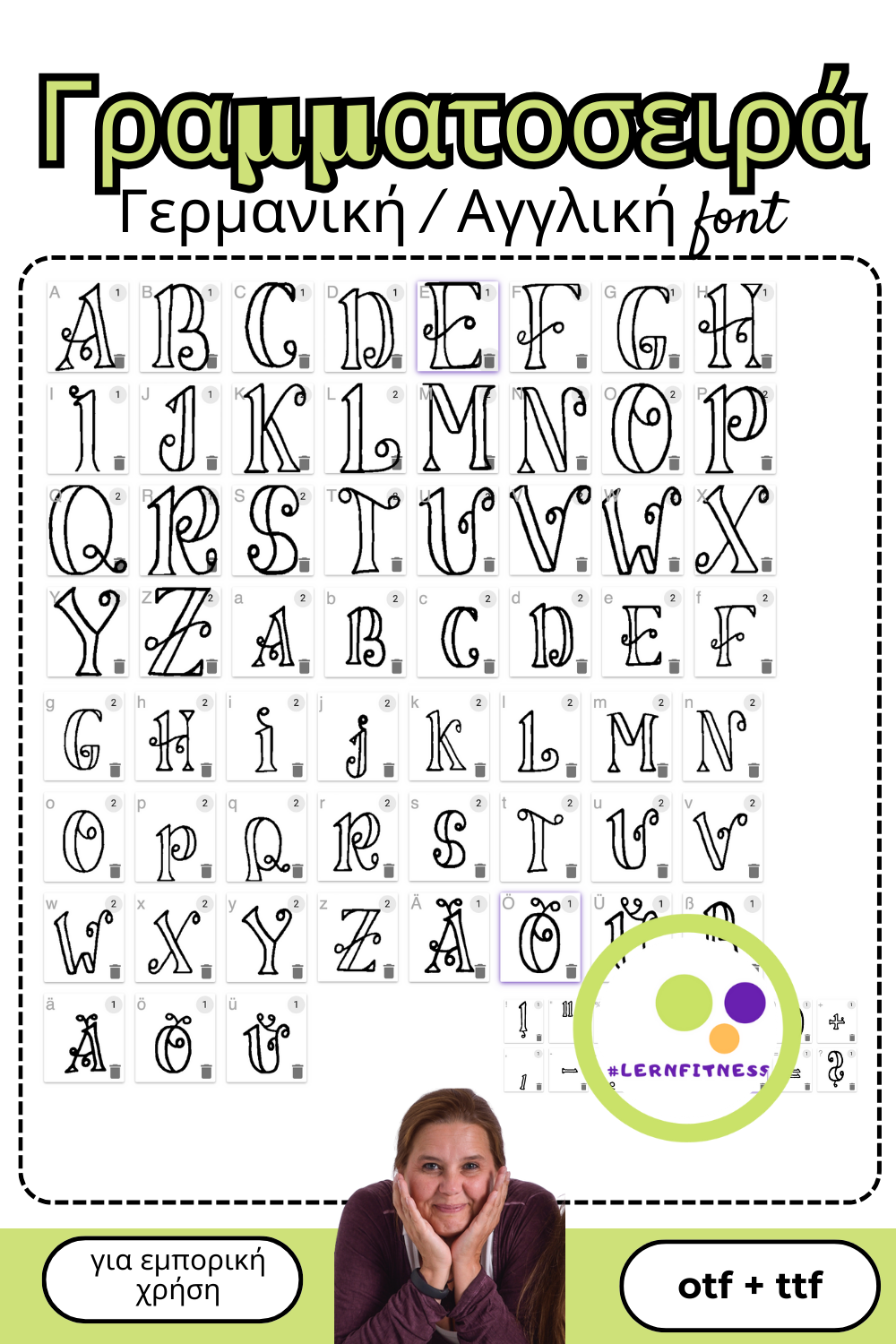
Γερμανική / Αγγλική font Lernfitness Ornament | για εμπορική χρήση | διακοσμητική γραμματοσειρά | Γραμματοσειρές
Αυτή η γραμματοσειρά σχεδιάστηκε από εμένα με αγάπη.
Αποτελείται από όλα τα γράμματα που χρησιμοποιούνται συνήθως στη Γερμανία, συμπεριλαμβανομένων των umlauts ä, ö, ü